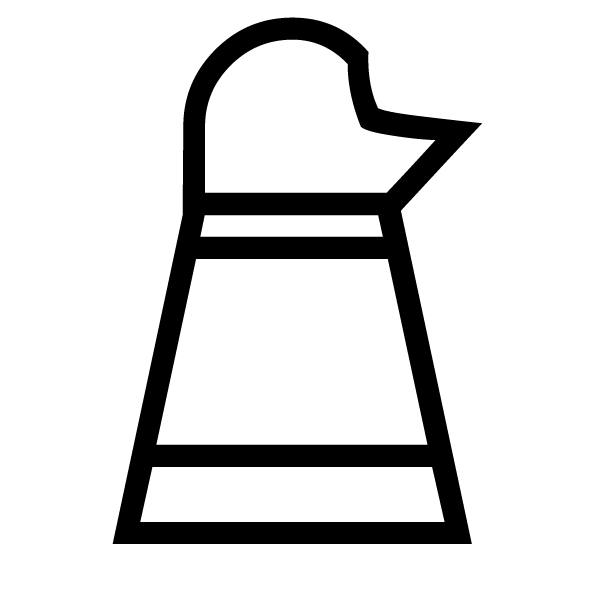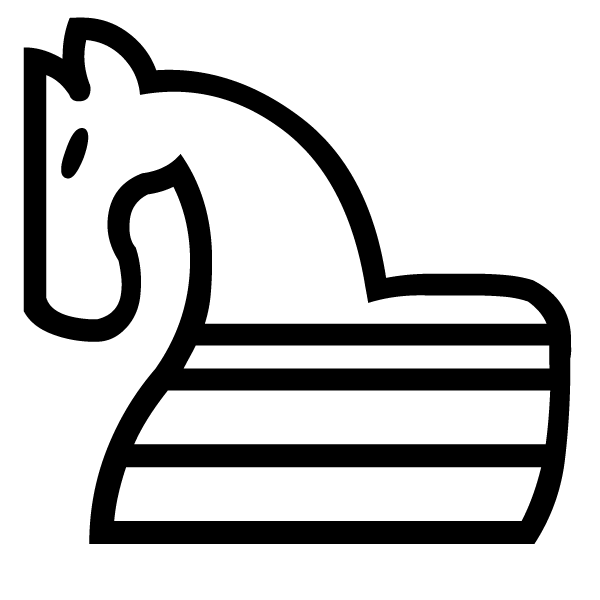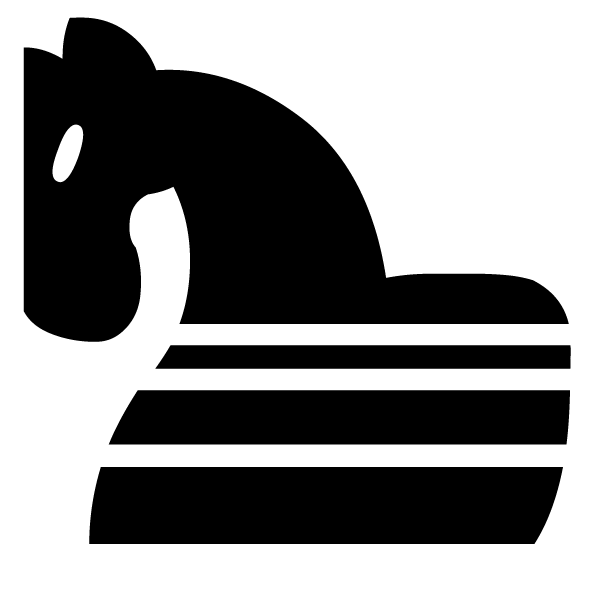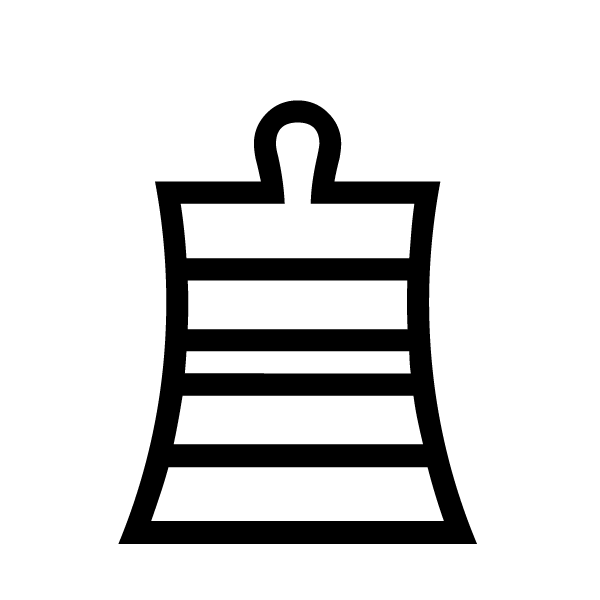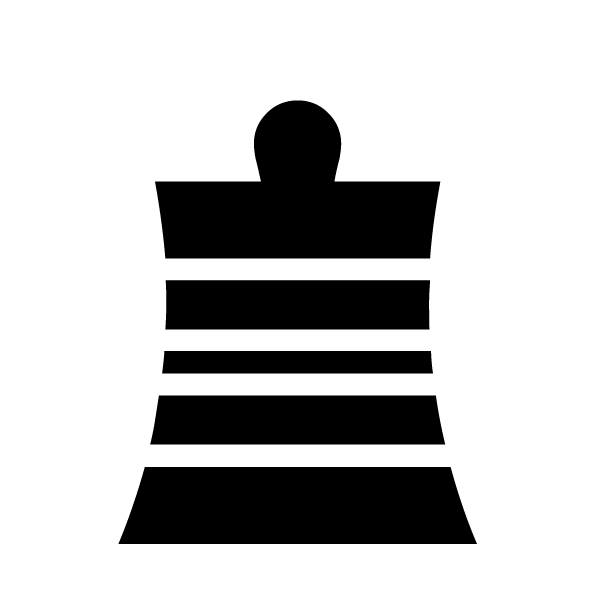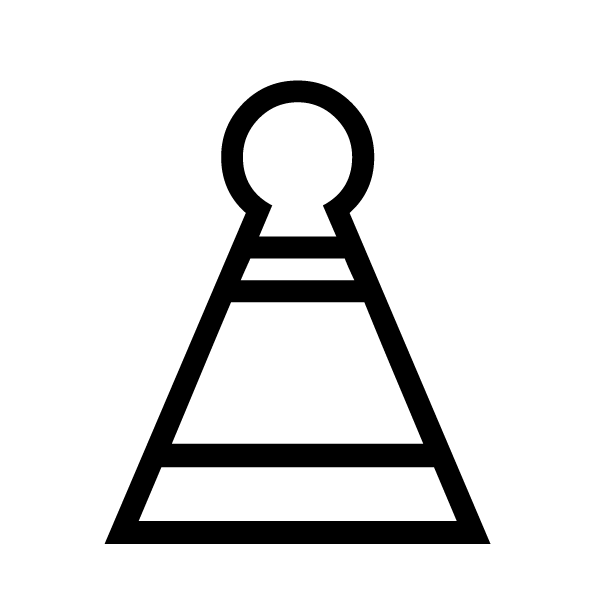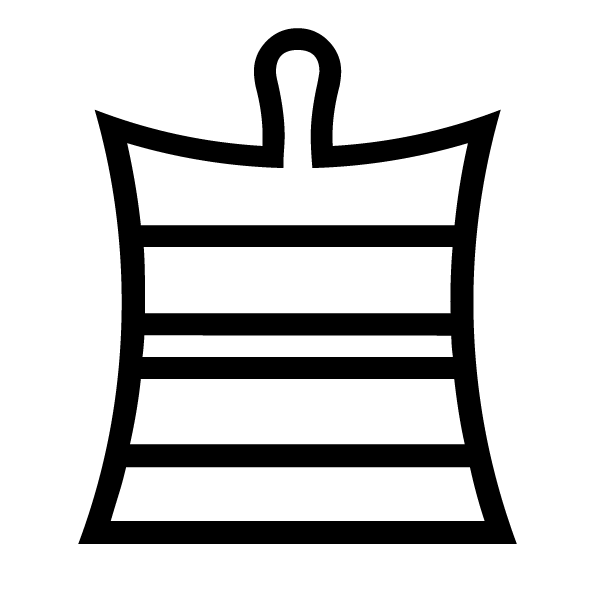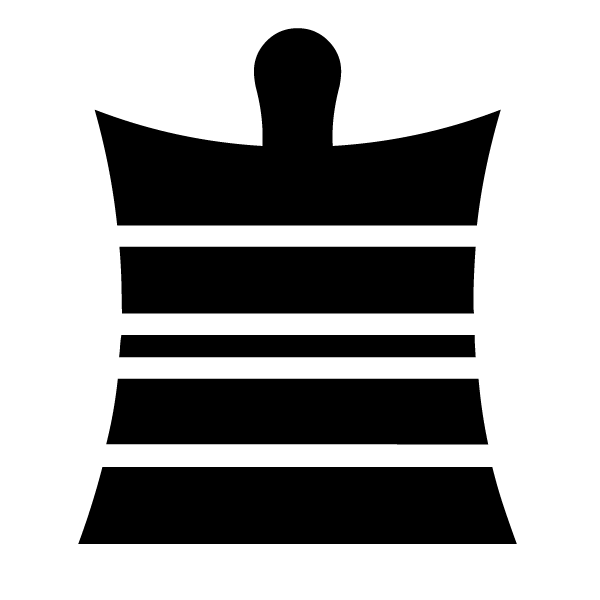
La Fuente Chess Alfonso-X es una obra inspirada en las piezas de ajedrez representadas en el «Libro de los Juegos» encargado por Alfonso X de Castilla, también conocido como el Sabio, entre los años 1252 y 1284.
Esta fuente se distingue por sus rayas horizontales, un estilo medieval único, y el particular diseño con picos en la parte superior de la torre y del alfil.
Imagen del Libro de los juegos encargado por Alfonso X de Castilla «el Sabio» entre 1252 y 1284 con las particulares piezas de ajedrez de la presente fuente
Juego de Ajedrez con la Fuente Alfonso-X: